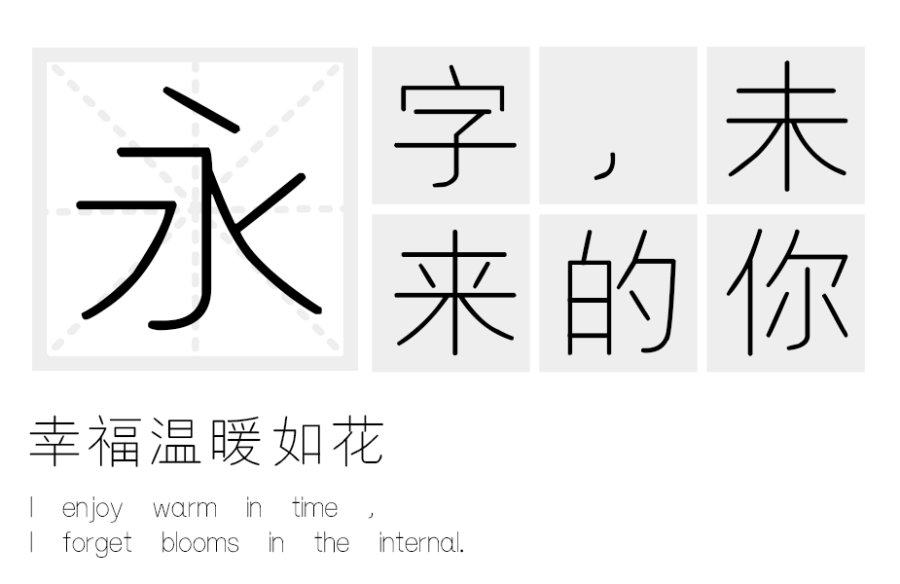
汉标细圆体发布
字体名称:汉标细圆体
字体类别:圆体
适用场景:文艺类的书刊、品牌广告和产品包装设计,以及社交网络的个性化用字
汉标细圆体简介:汉标细圆体字体是一款适合广告海报艺术设计的字体,该字体字形圆润饱满,用笔简洁,有满满的可爱小女生的气息。适用于文艺类的书刊、品牌广告和产品包装设计,以及社交网络的个性化用字。
汉标细圆体预览图展示: